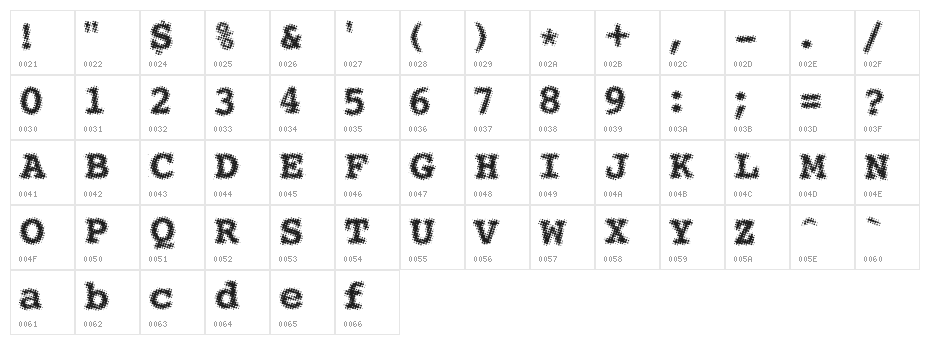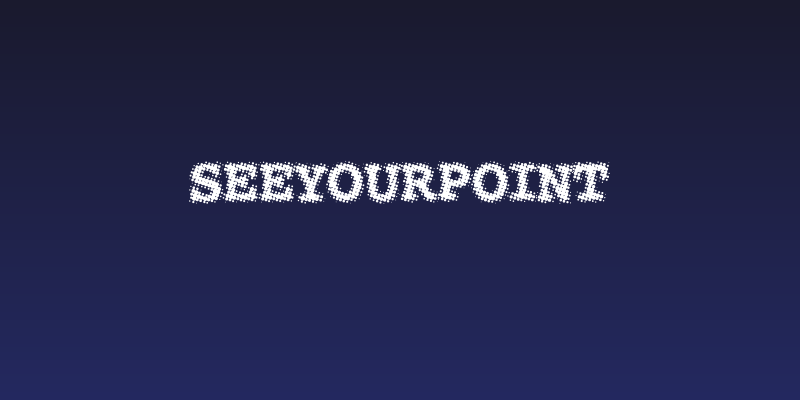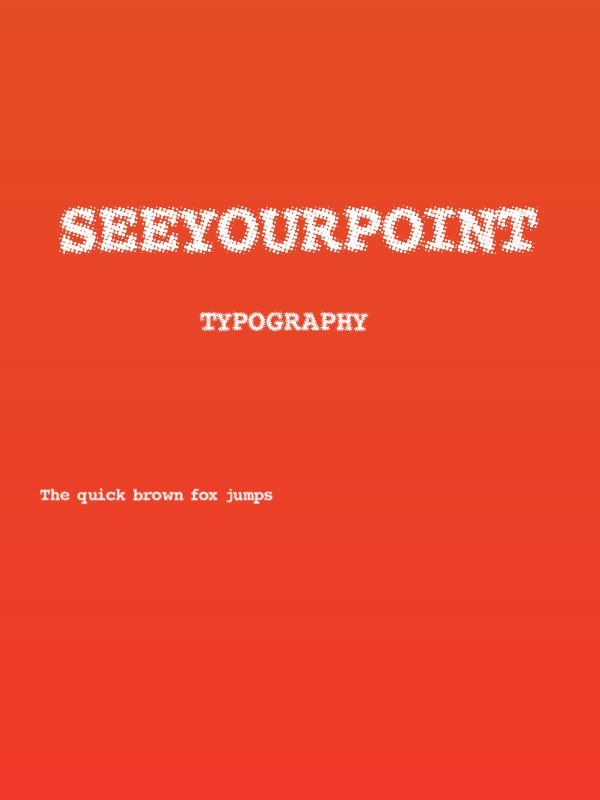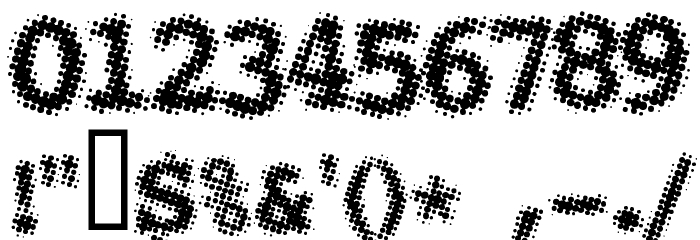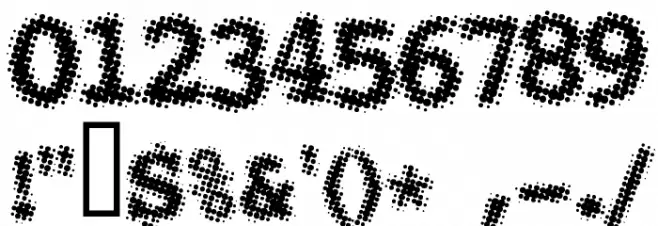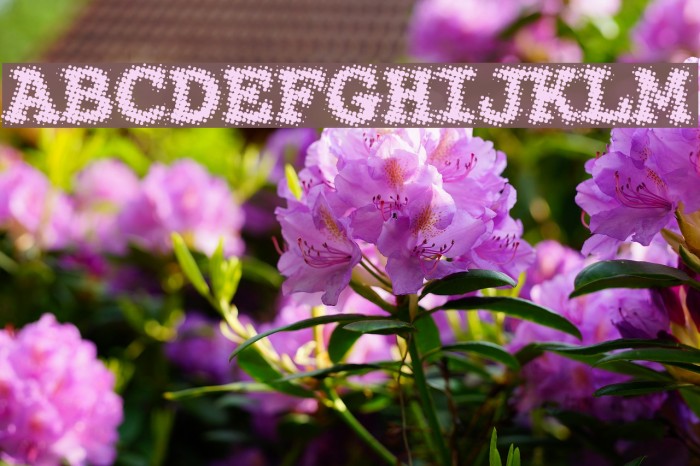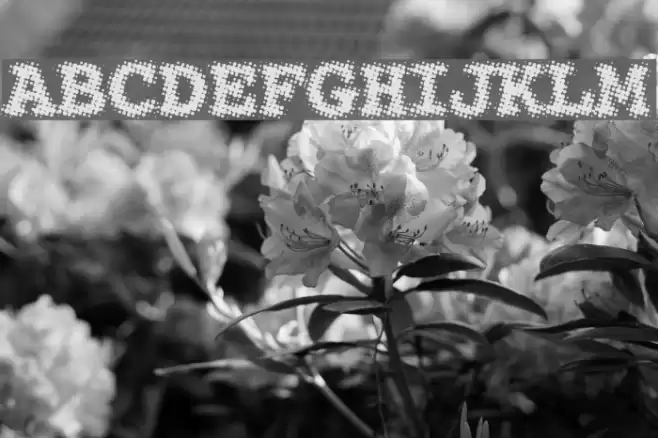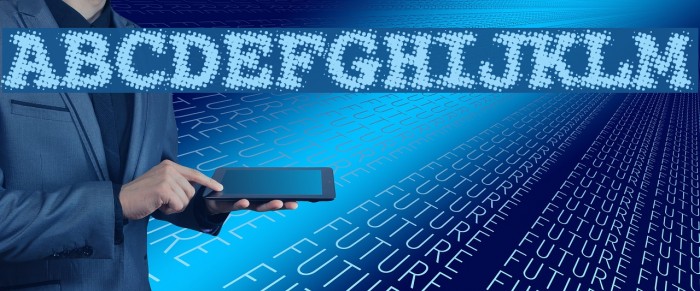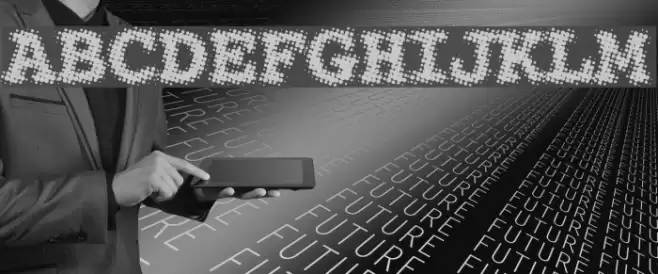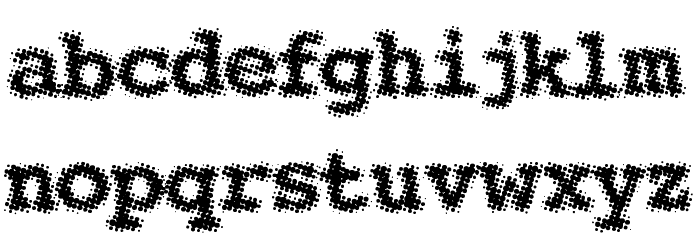
SeeYourPoint Font
| Vorgeschlagene Projekte | Ideal for posters, album covers, digital art, and branding that requires a modern and artistic touch. |